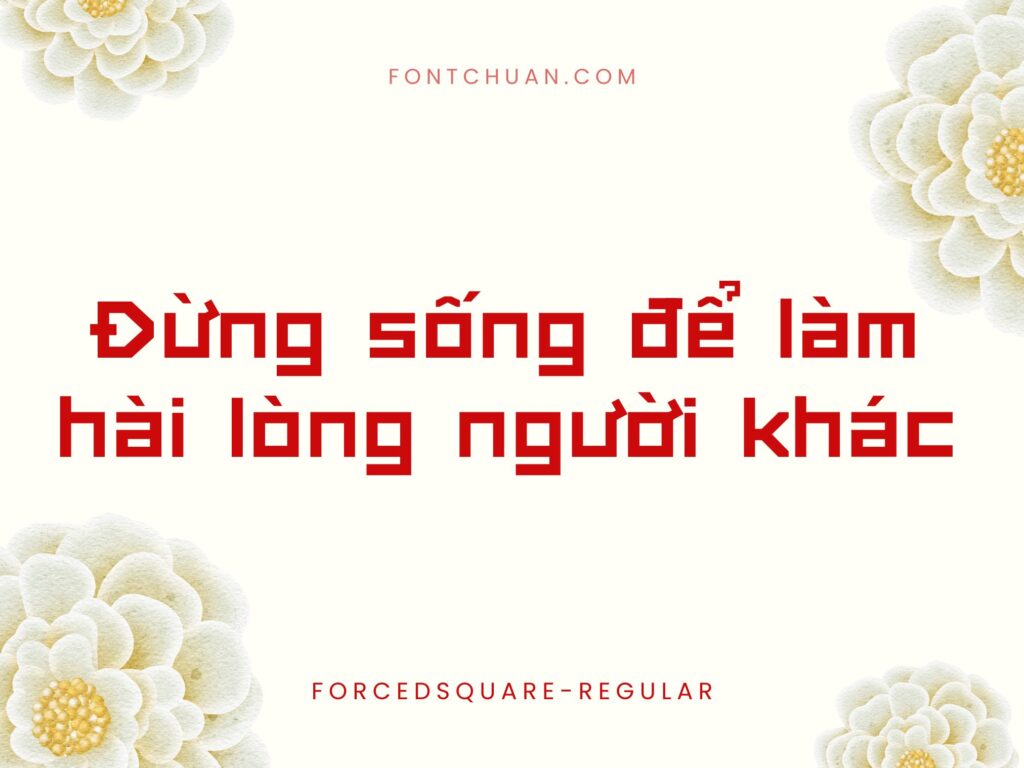
Font Force Square Việt Hóa
Tác giả Font: Drawperfect
Việt hóa bởi: Zenis
Forced Square là một phông chữ thuộc thể loại Techno với phong cách hình vuông, được thiết kế bởi DrawPerfect. Phông chữ này có thiết kế hình học và góc cạnh, đặc trưng bởi vẻ ngoài vuông vức và khối, với các chữ cái được cấu trúc bằng các đường thẳng và góc sắc nét, mang lại cảm giác hiện đại và tương lai. Các ký tự in hoa và in thường duy trì chiều rộng nhất quán, tạo nên một diện mạo đồng nhất. Các chữ số và ký tự đặc biệt tuân theo cùng nguyên tắc thiết kế, đảm bảo sự thống nhất trong toàn bộ phông chữ. Phong cách đậm và có cấu trúc của phông chữ này làm cho nó có tính dễ đọc cao và tạo ấn tượng mạnh mẽ, phù hợp cho nhiều ứng dụng thiết kế khác nhau. Forced Square miễn phí cho cả mục đích sử dụng cá nhân và thương mại, giúp người dùng linh hoạt trong việc áp dụng phông chữ này vào các dự án khác nhau. Về ứng dụng, phông chữ này lý tưởng cho việc xây dựng thương hiệu công nghệ, tiêu đề trò chơi video, áp phích và giao diện kỹ thuật số. Về ngành nghề, Forced Square đặc biệt phù hợp với lĩnh vực quảng cáo, công nghệ và giáo dục, nơi cần sự rõ ràng và hiện đại trong thiết kế.